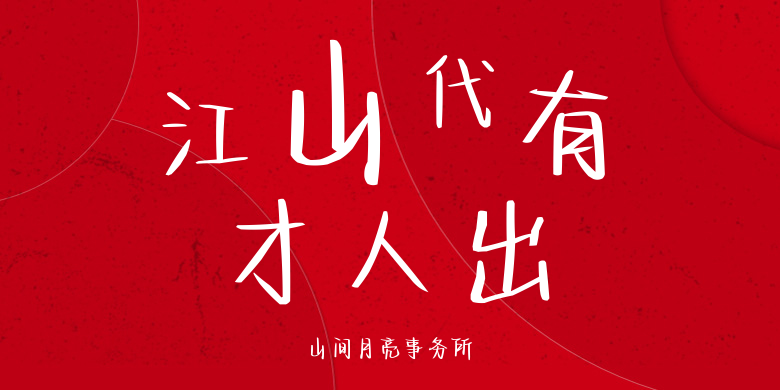
山间月亮事务所
山间月亮事务所,这款字体结构工整、笔画清晰,兼顾美观与易读性,适用于标题、正文、海报、包装、LOGO 等多种场景。字形优雅稳定,风格百搭耐看,适配日常排版与创意设计,让文字呈现更舒适、更具质感。山间月亮事务所一笔一画,皆是细节,以均衡的比例、流畅的线条打造舒适视觉体验,字形端正大气,风格简约现代。无论是商业设计、品牌宣传还是日常排版,都能轻松驾驭,让文字更有格调与力量。山间月亮事务所字体下载。